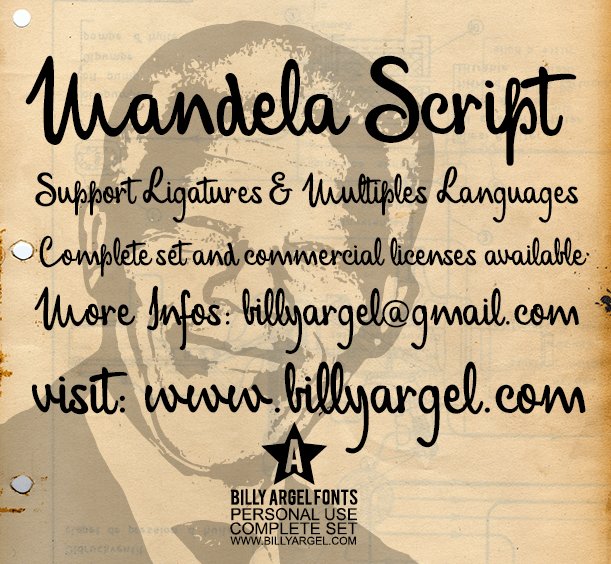
Mandela Script Font – Download Grátis
Através do talento dos designers independentes Hamilton, a fonte Mandela Script é uma escolha inspiradora para aqueles que buscam uma fonte à mão com um toque elegante e sofisticado. Esta descrita como parte de uma série handwritten fonts está disponível de forma gratuita para uso pessoal. Para quem necessita da fonte em versões comerciais ou completas, Hamilton disponibiliza tais opções através do site billyargel.com onde também encontrará mais informações sobre como adquirir esses produtos. Não deixe de visitar o site e explorar a vasta coleção de fonts disponíveis por lá.